今回は「族」の書き方を解説します。
「族」の見本
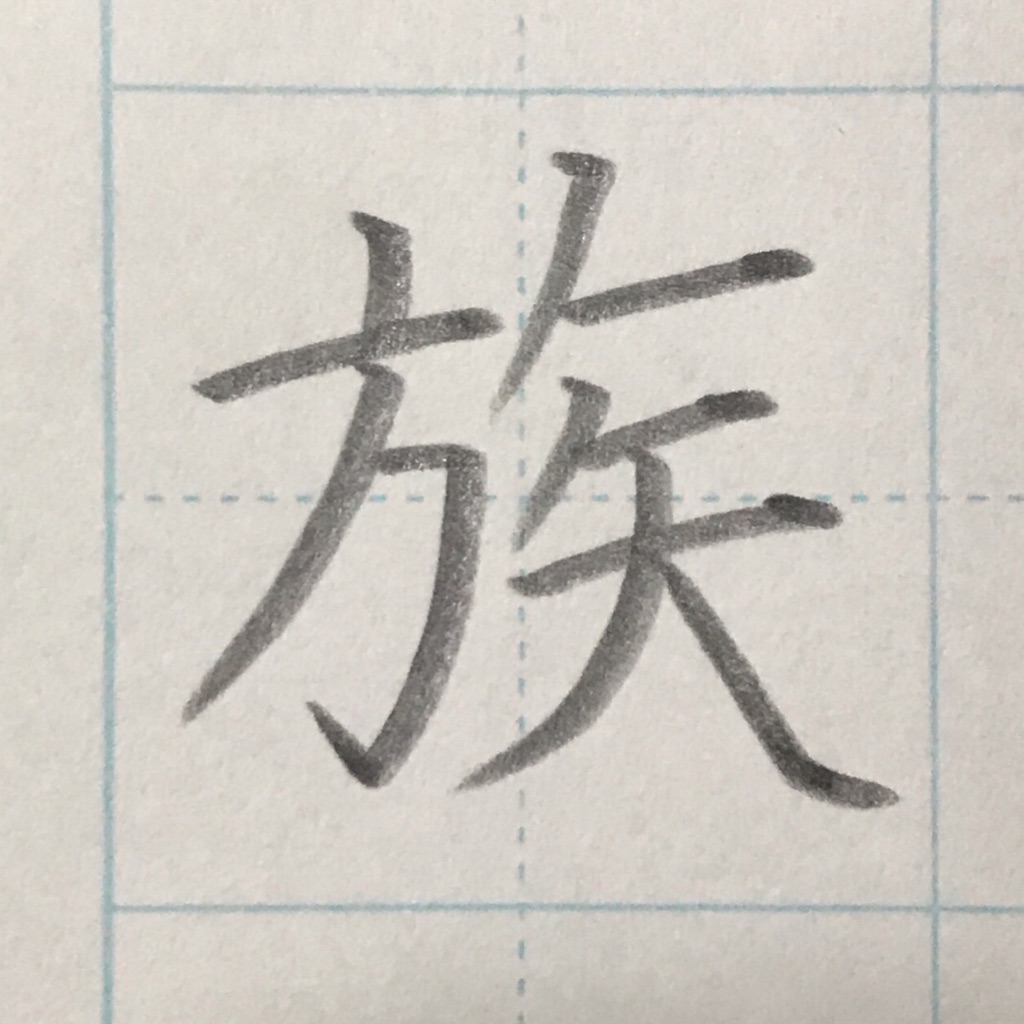
「族」の書き順
11画です。3、4画目の順番に注意!
「族」のポイント
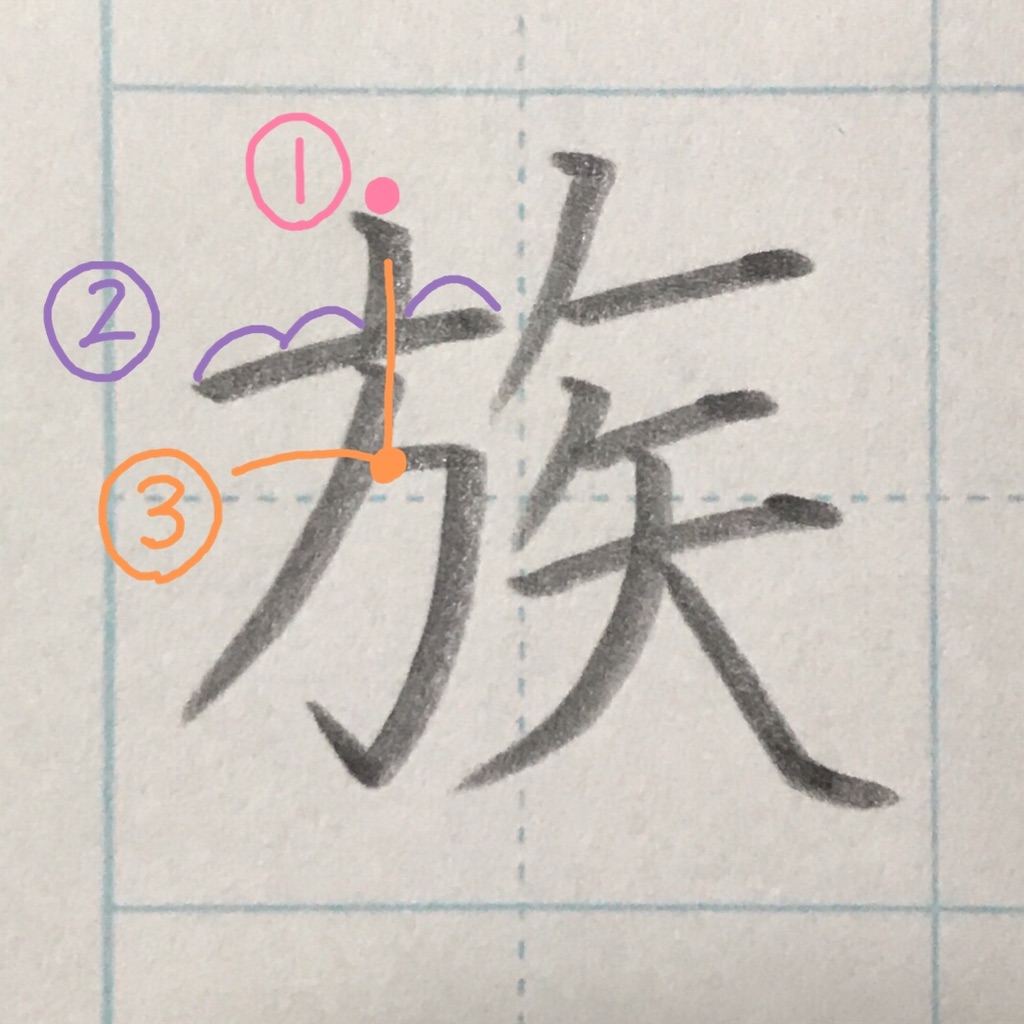
①1画目の点は、まっすぐでもナナメ(45°)でもOK。
②点を挟んで2対1にしましょう。右上がりに。
③3画目は点の真下からスタート。
(斜め点にする場合は、点の中心の真下から)
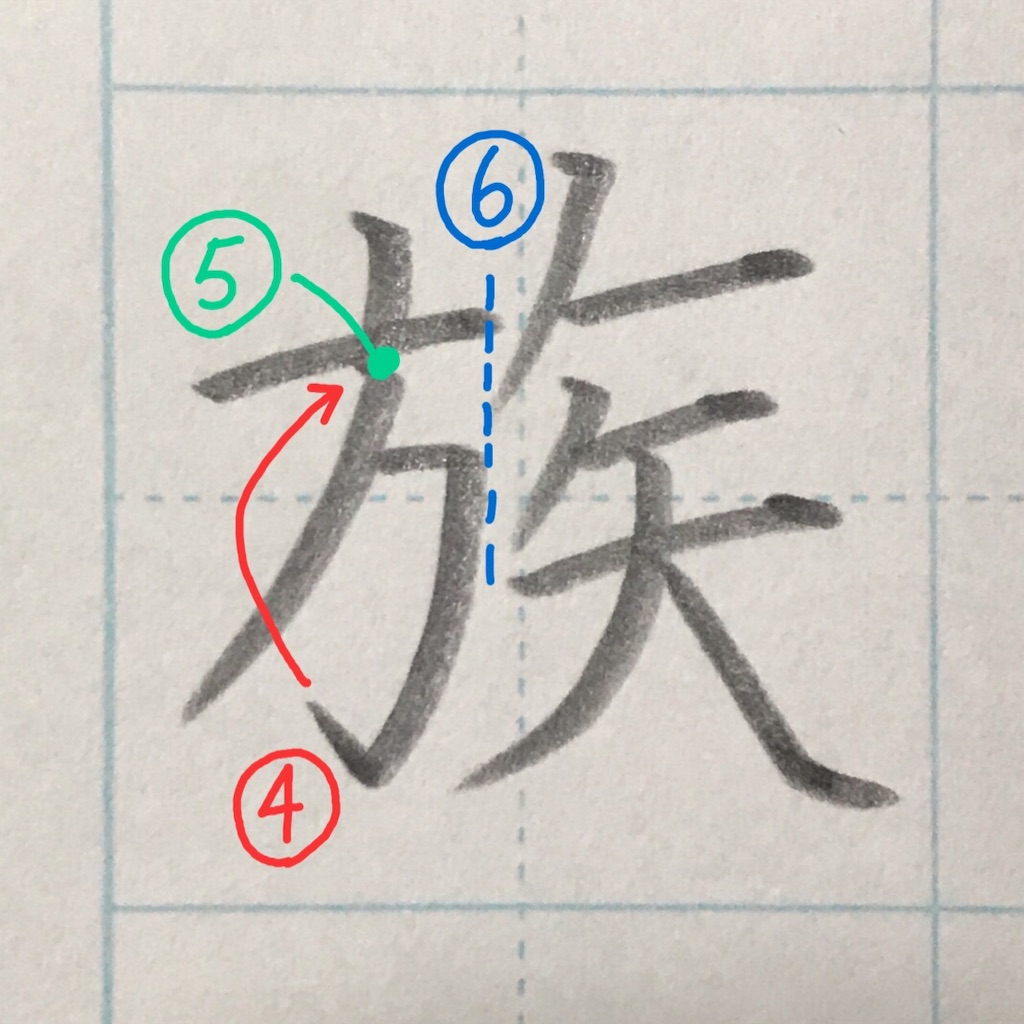
④ハネは次の画に向けて。
⑤4画目も点の真下からスタート。
(3画目のスタート位置が重要ですね!)
⑥「方」の右端は中心より少し左で揃える。
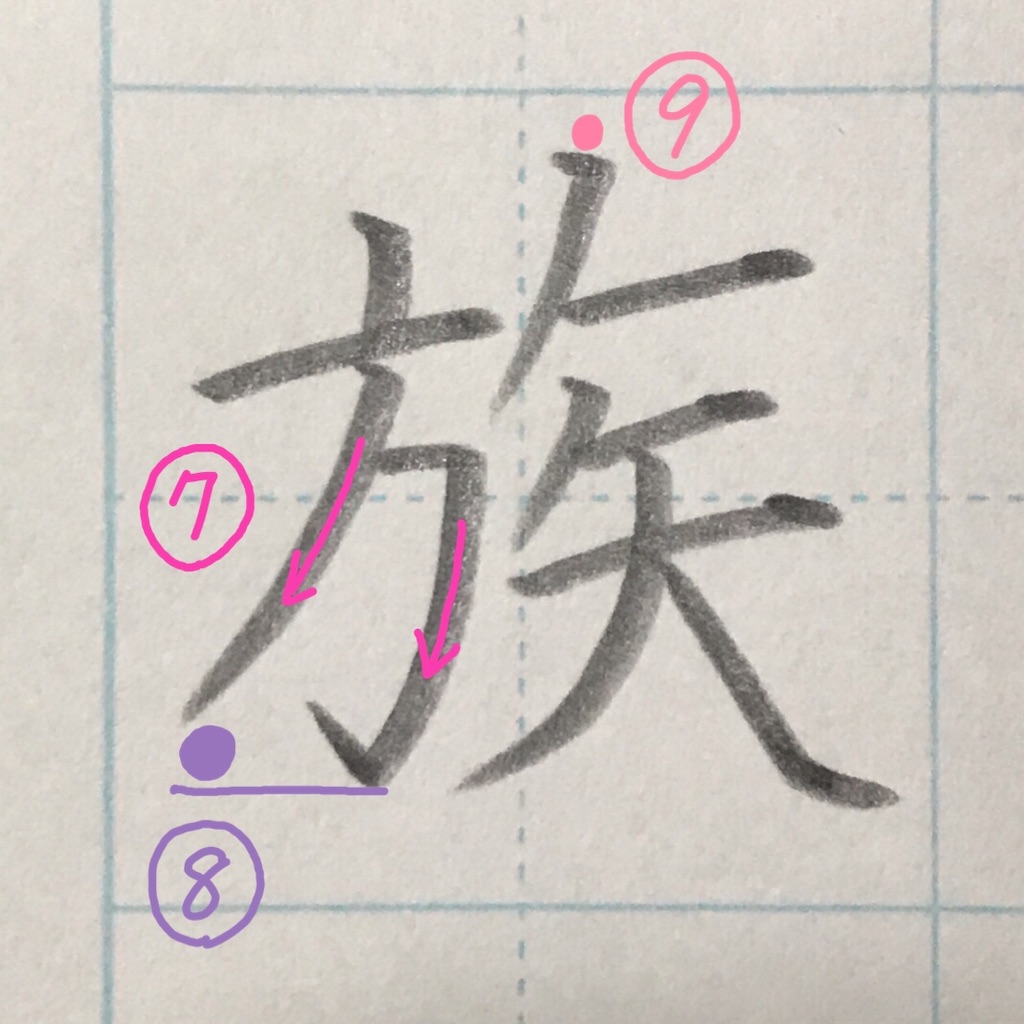
⑦ほんの少し広がる。(ほぼ平行でOKです。)
⑧余白を作る。
⑨高い位置からスタート。(30°くらい)
→そのためには、1画目のスタートを少し低くしておく必要があります。
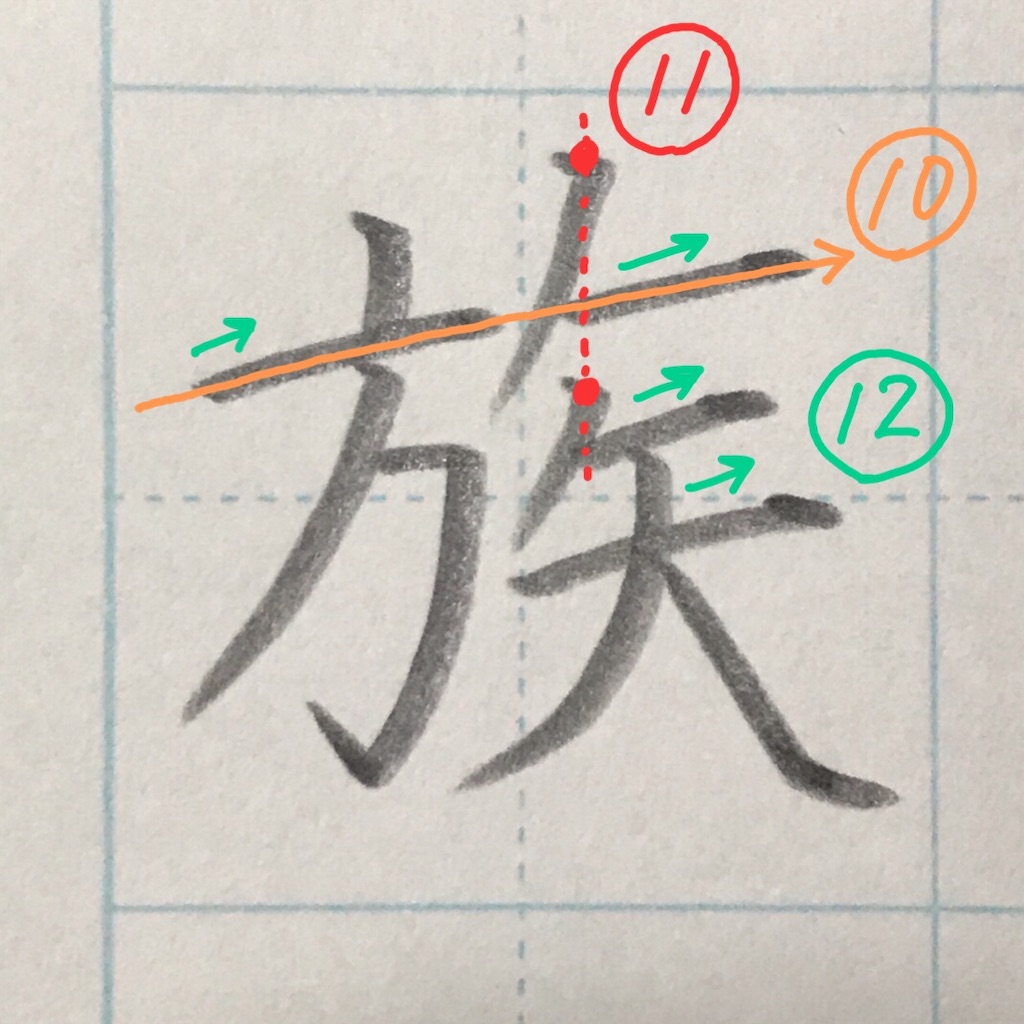
⑩2画目、6画目は右上がりに並べる。
⑪5画目、7画目の始まりを縦に揃える。
⑫横画は右上がりに揃えると◎。
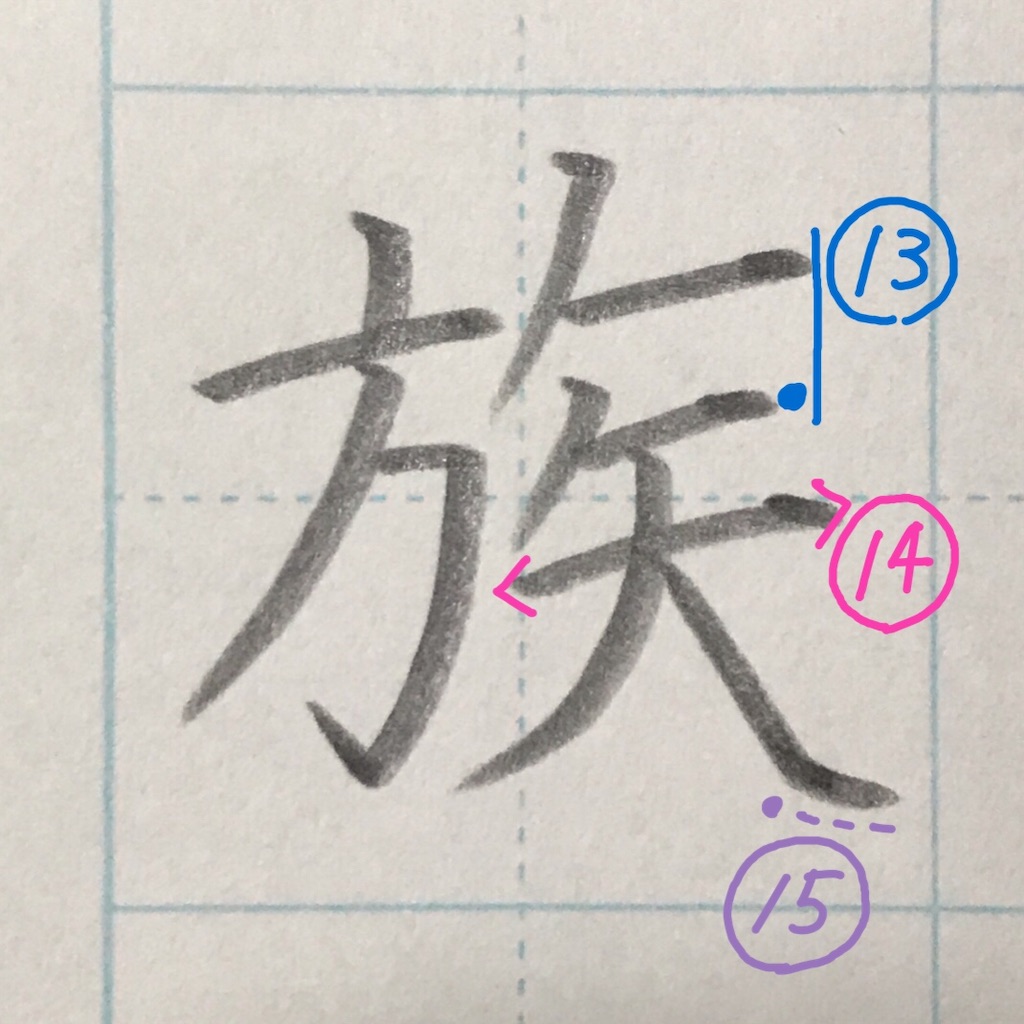
⑬8画目は少し短く。
⑭9画目は少し長く。
⑮止めて、払う。
こんなところも見てみましょう
a:払いが少し左へ出る。
b:3画目の角と8画目のスタートは大体高さが同じ。
c:下は揃える。
d:払いは右へ出してバランスをとる。
完成!